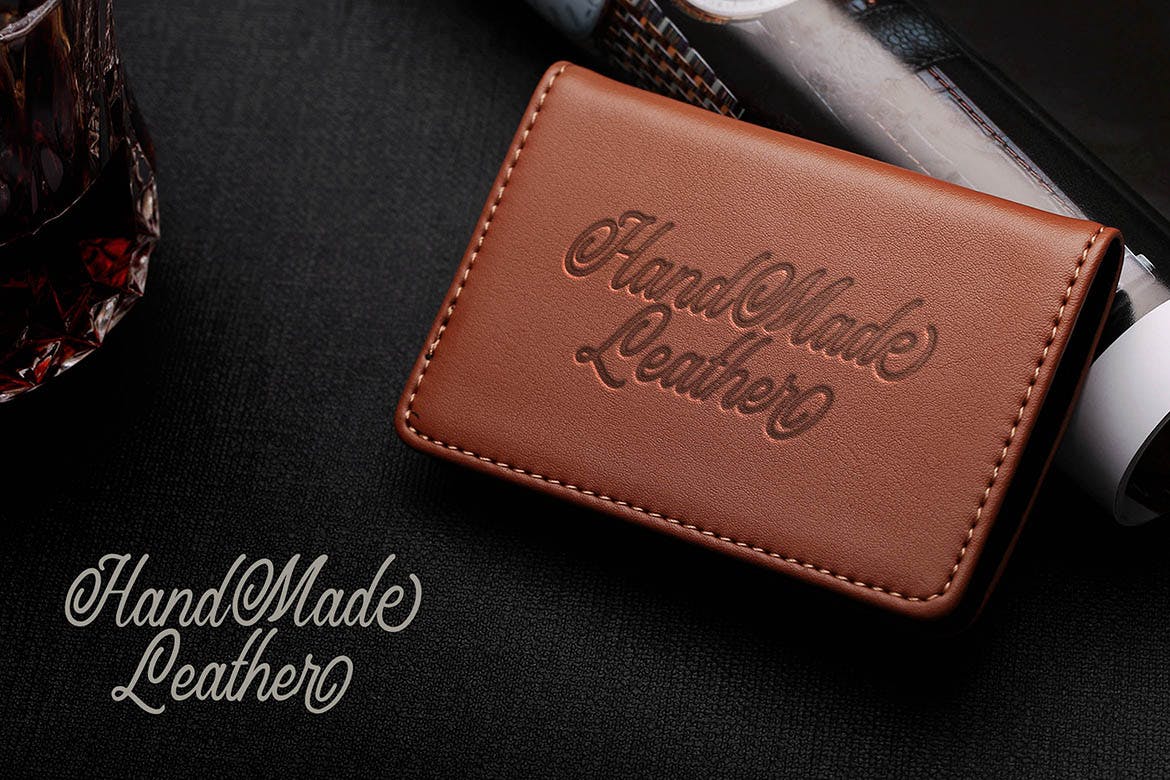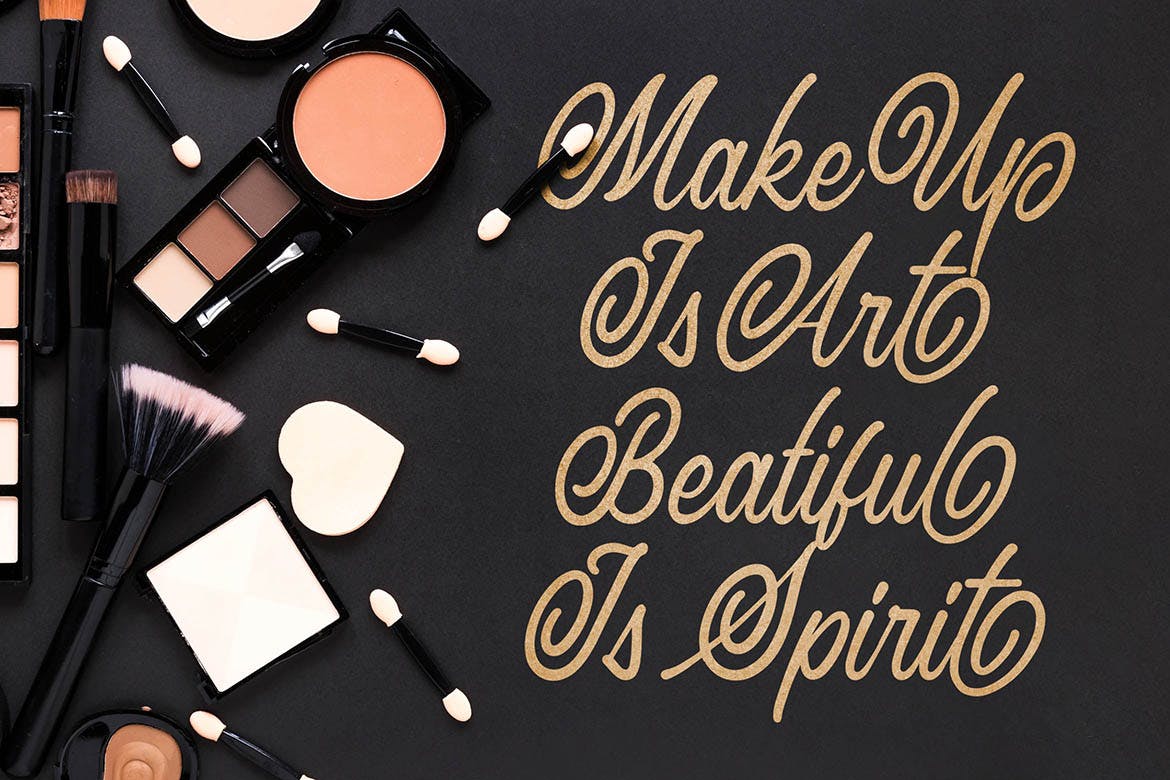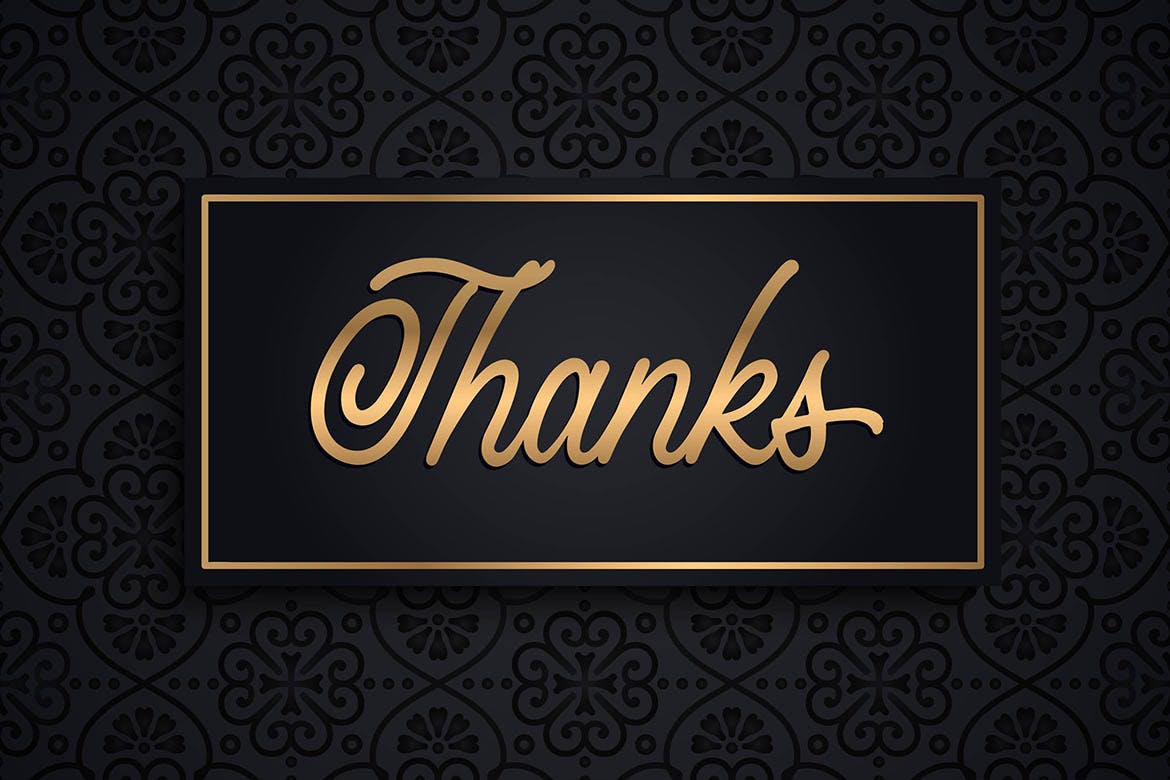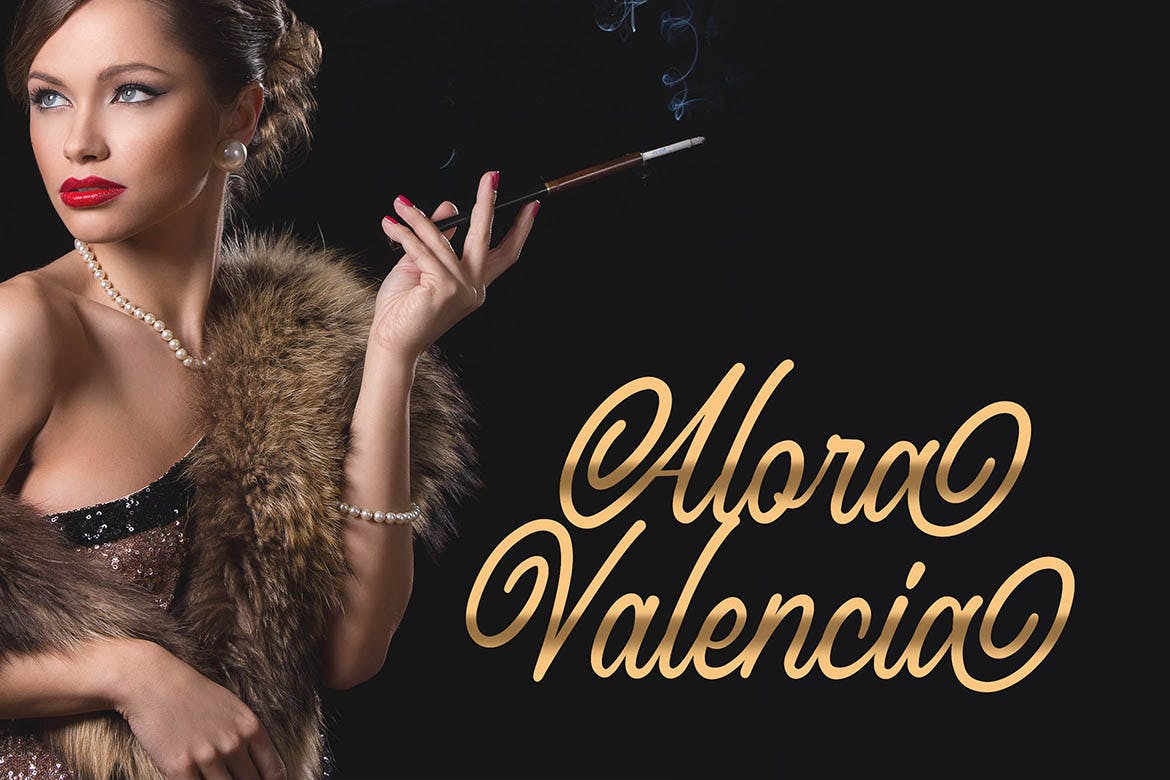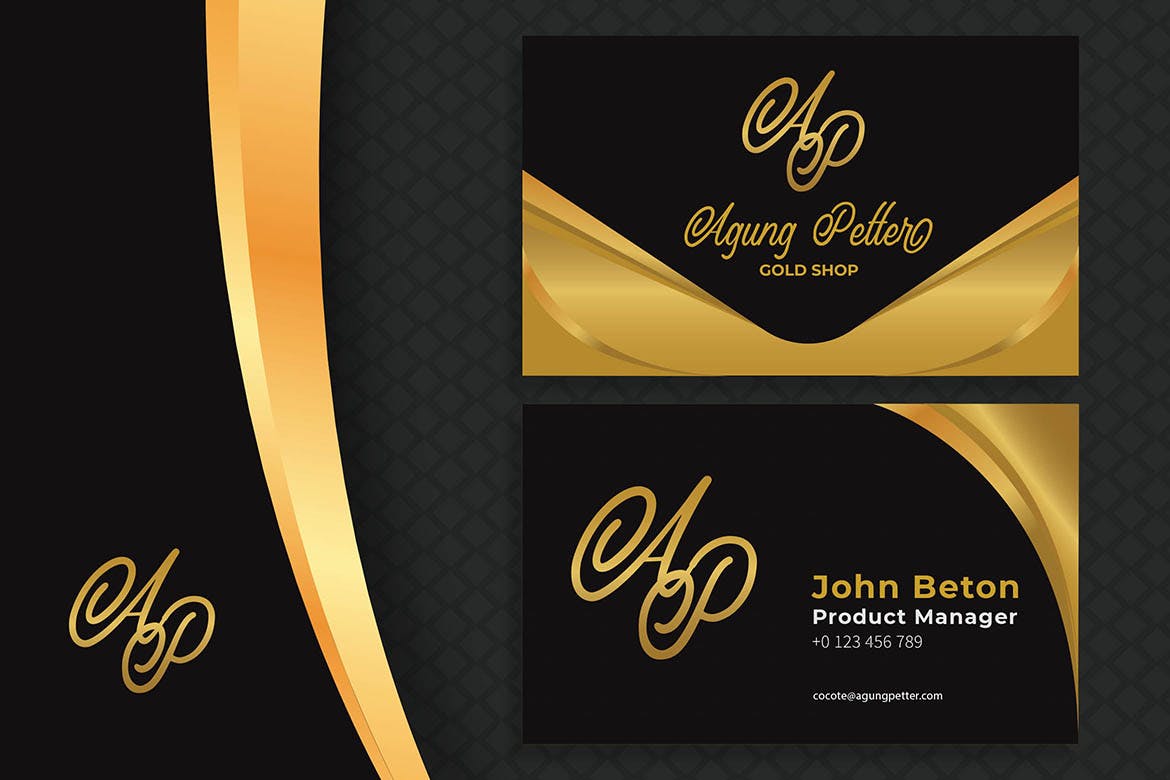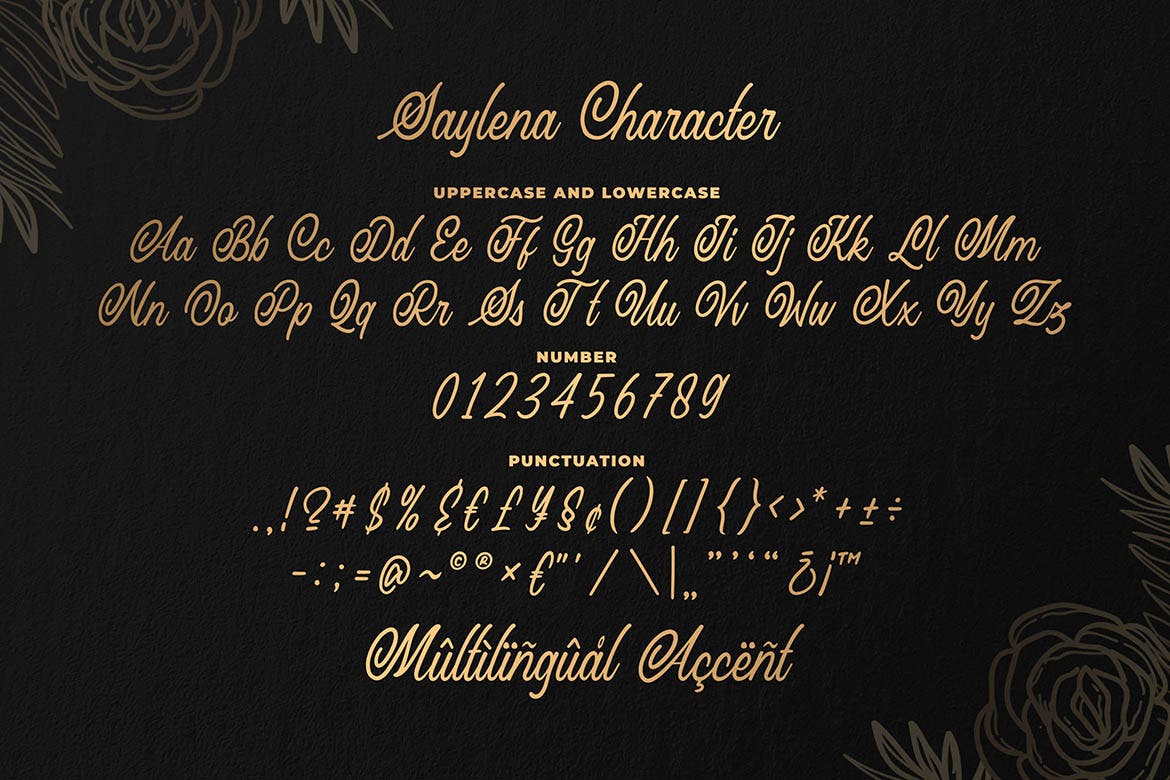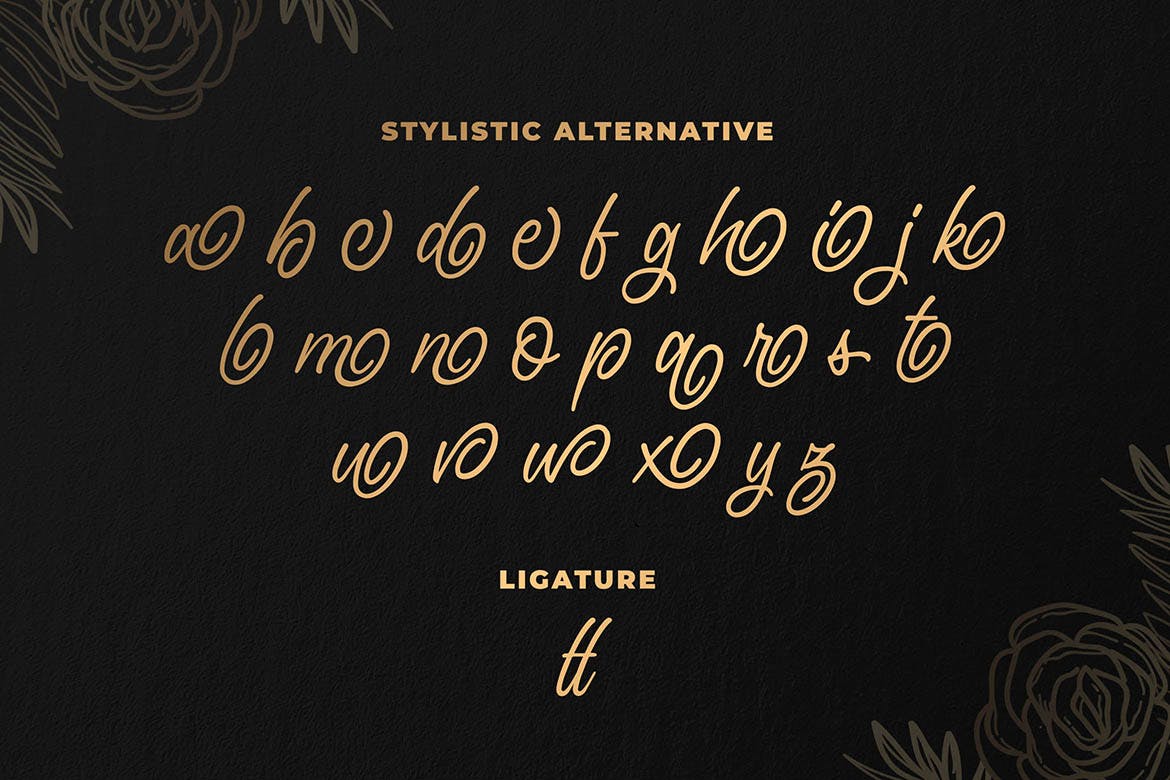
Saylena Luxury Script Font
فونت Saylena با طراحی لوکس و جذاب، مناسب برای پروژه‌های مختلف.
ما به شما فونت جدید و لوکس Saylena را معرفی می‌کنیم. این فونت با الهام از سبک اسکریپت لوکس طراحی شده و برای امضای شخصی، پوستر، مد، عروسی، برندینگ و غیره بسیار مناسب است.
ویژگی‌های چند زبانه:
ŽžŠŒšŸÀÁÂÃÄÅÆÇÈÉÊËÌÍÎÏÐŁÑÒÓÔÕÖØÙÚÛÜÝßàáâãäåæçèéêëìíîïłñòóôõöøùúûüýÿ
ویژگی‌ها:
• حروف بزرگ
• حروف کوچک
• اعداد
• نشانه‌گذاری
• چند زبانه
• کدگذاری PUA
• OpenType